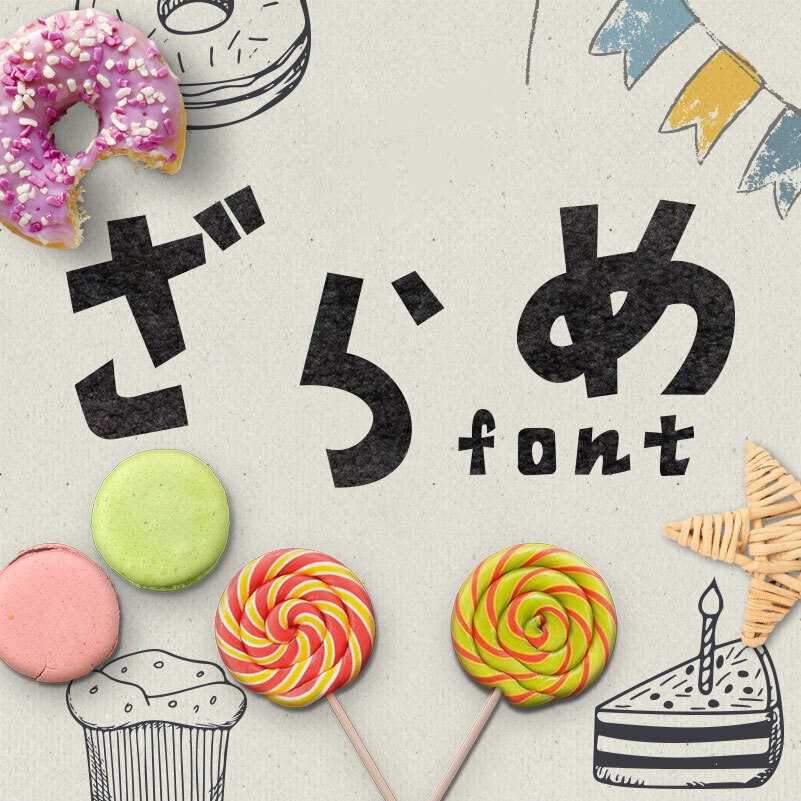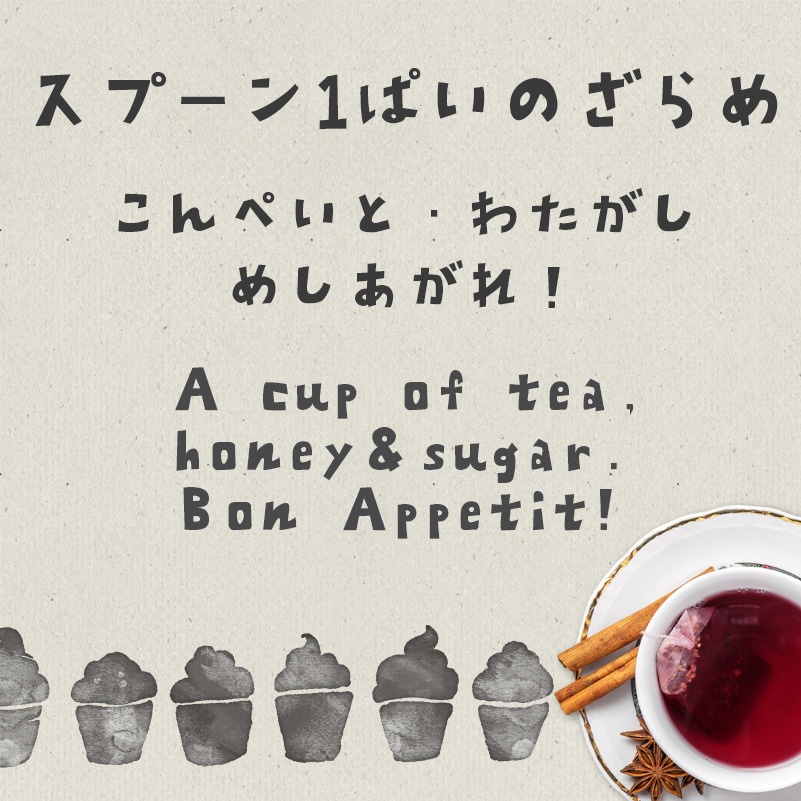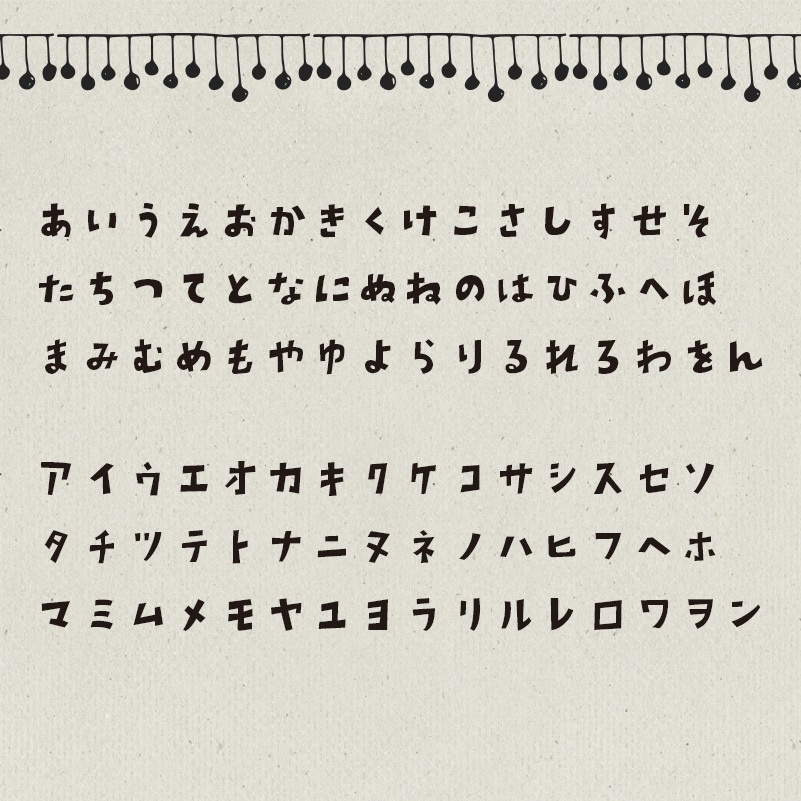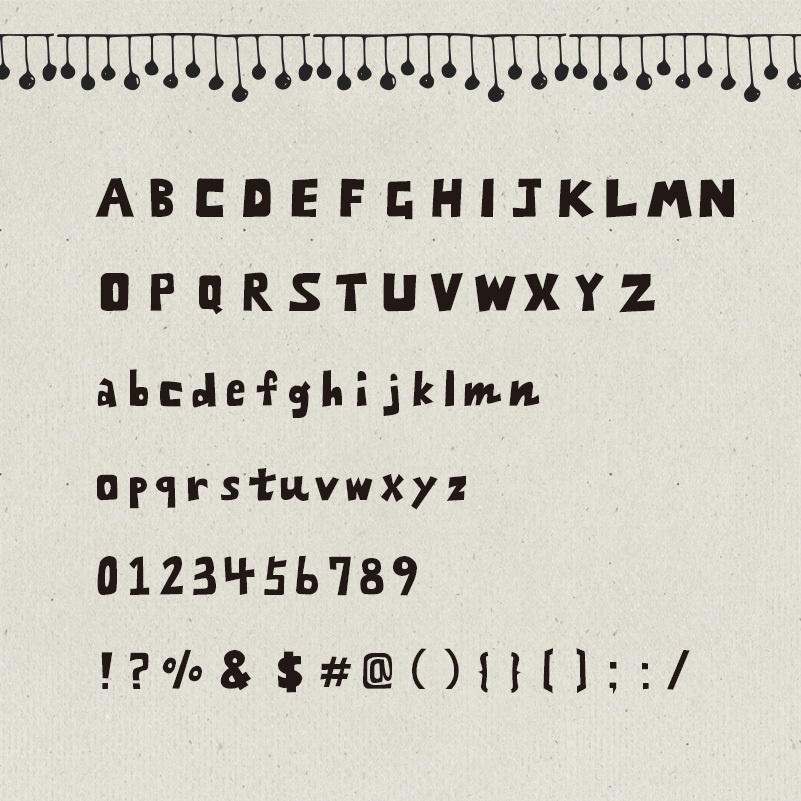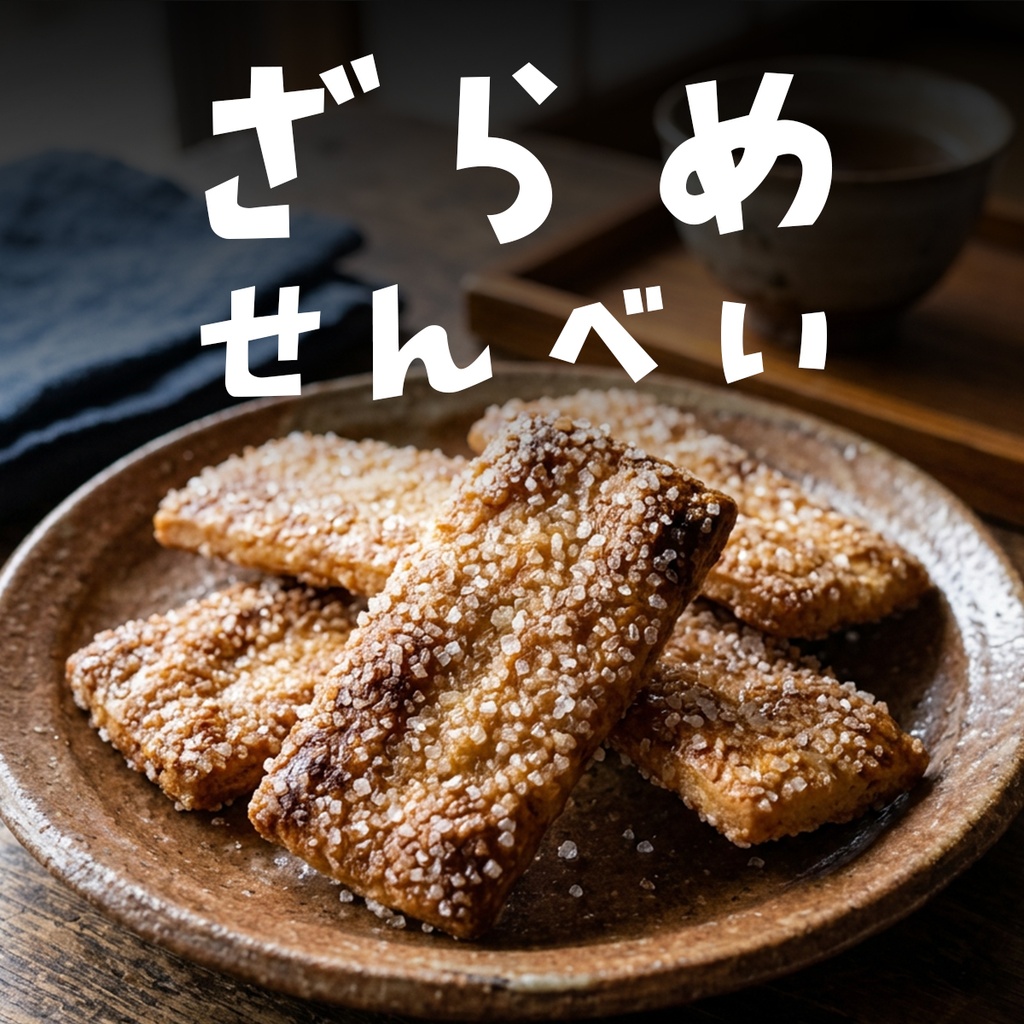
【商用可・縦書き対応】ざらめフォント ひらがな・カタカナ・アルファベット収録 手書きPOP書体
【商用可・縦書き対応】ざらめフォント
お菓子づくりにかかせないザラメ糖をイメージしたフォント。 ザクッとした手書きの風合いのある少し太めのラインが特徴。 見出しや目立たせたいところにぴったり。 アナログでかわいくてオリジナル性のあるデザインをめざす方に! 商用利用OKです。 ひらがな・カタカナ・アルファベット・記号 収録 フォント形式:OpenTypeフォント 【動作環境】Windows / Mac 対応 【インストール方法】 Windows:ダウンロードしたZIPを解凍し、.otfファイルを右クリック→「インストール」 Mac:Font Bookにファイルをドラッグ&ドロップ ▼ まず試してみたい方へ ・無料お試し版(英数字・記号のみ)→ https://vanillabeanz.booth.pm/items/714802